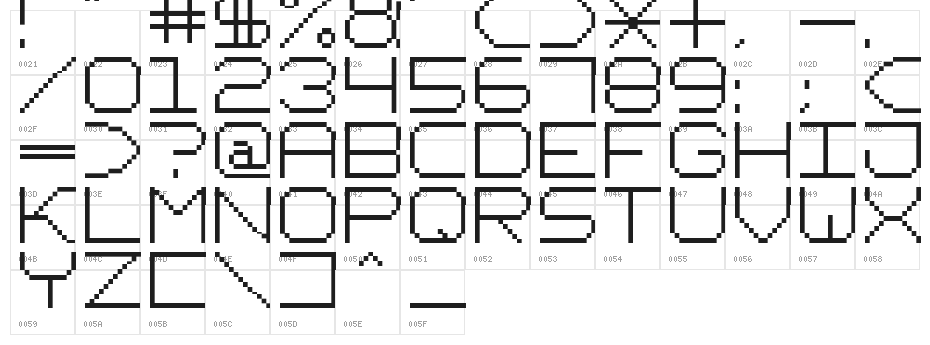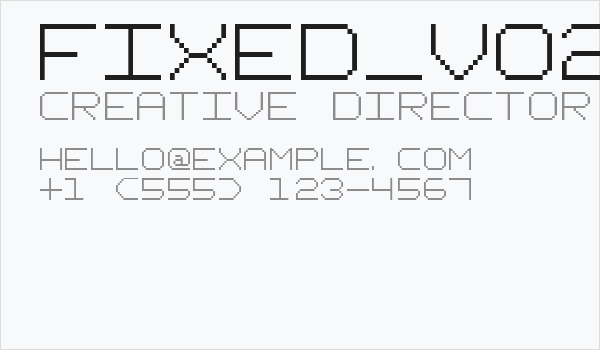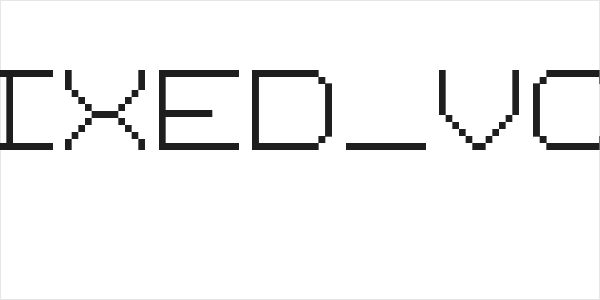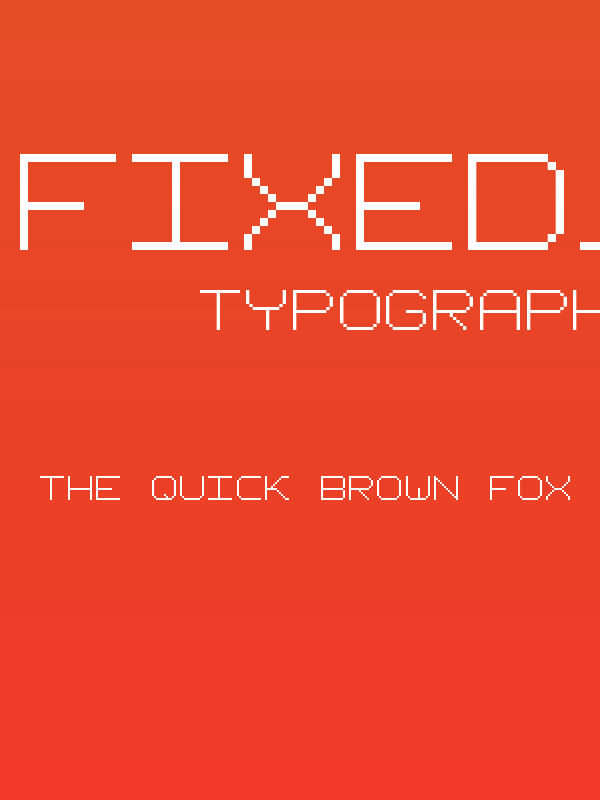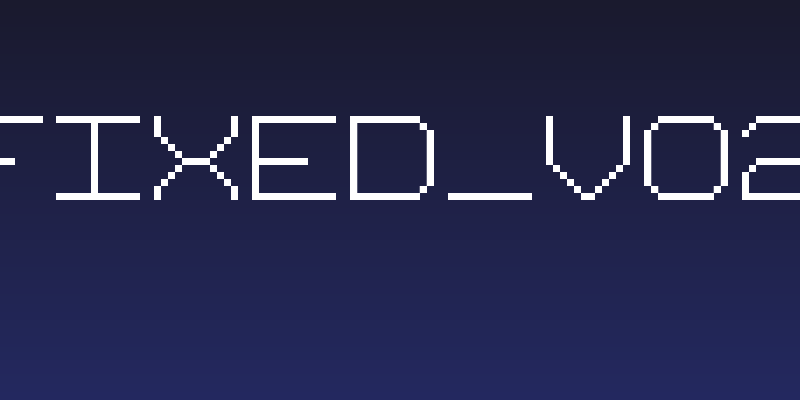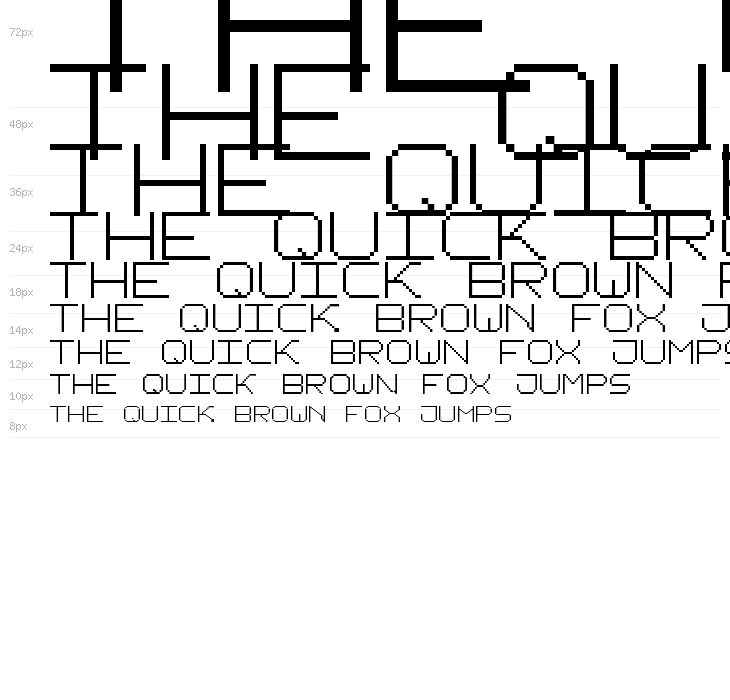
fixed_v02 Font
| カテゴリ | Pixel |
| 文字間隔 | Normal |
| 全体的なスタイル | Retro, Digital |
| 用途 | Logos, Headlines, Digital displays |
| おすすめプロジェクト | Ideal for video game design, tech-themed posters, retro digital displays, and any project seeking a nostalgic or technological vibe. |
| 等幅 | Yes |